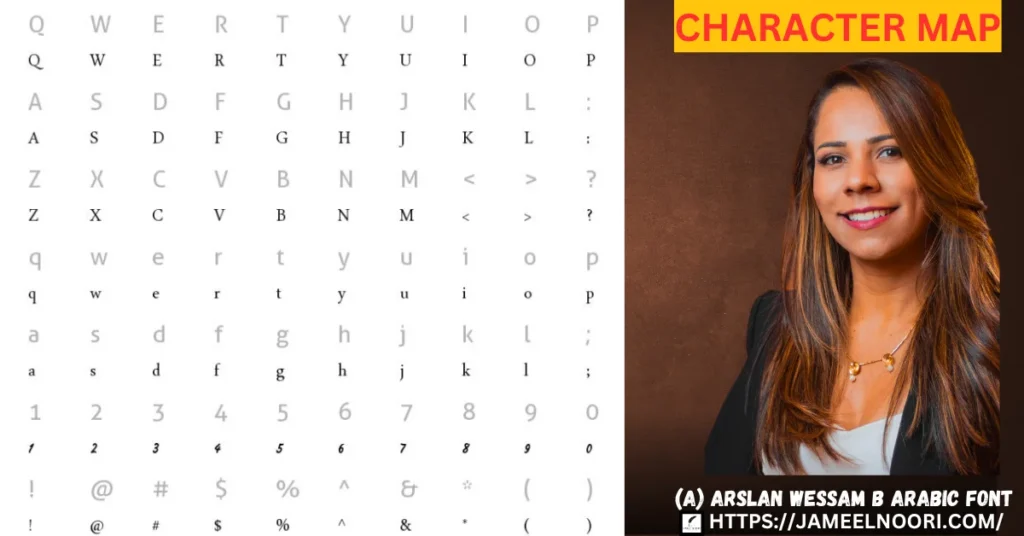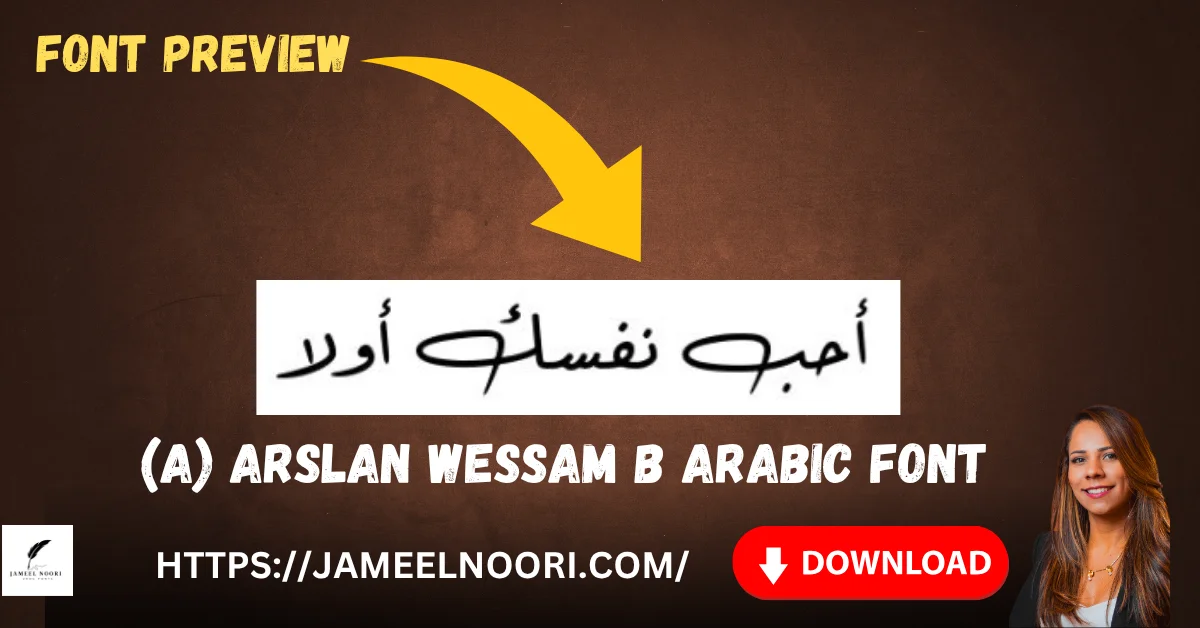
What is (A) Arslan Wessam B Arabic Font?
(A) Arslan Wessam B Arabic Font ek versatile Arabic font hai jo Arabic script se inspire hai. Ye font Urdu script ke similar characters adopt karta hai aur har type ke Arabic writing style ke liye compatible hai.
- Elegant and professional Arabic calligraphy
- Ideal for posters, messages, presentations
(A) Arslan Wessam B Arabic Font ka use karke aap apne designs aur presentations ko professional aur eye-catching bana sakte hain. Ye font designers aur content creators ke liye best option hai.
- High readability for Urdu and Arabic text
- Multiple writing styles supported
- Perfect for social media posts and graphics
Character Map section me aap font ke har character aur calligraphy style ko detail me dekh sakte hain. Ye feature designers ke liye bohot helpful hai.
Why A Arslan Wessam B Arabic Font is Best Choice in Pakistan
Pakistan me Urdu fonts aur Arabic fonts ka use educational aur design purposes me ziada hota hai. (A) Arslan Wessam B Arabic Font ko select karne ki wajah ye hai:
- Best Arabic font for presentations and posters
- Compatible with Urdu fonts for easy writing
- Widely used in Lahore, Karachi, and Islamabad
- Perfect for Islamic calligraphy projects
(A) Arslan Wessam B Arabic Font ek ultimate choice hai un logo ke liye jo Urdu aur Arabic fonts me professional aur stylish designs create karna chahte hain. Ye font highly readable, versatile, aur easy to install hai. Aap chahe social media post banayein ya PowerPoint presentation design karein, ye font aap ki har requirement ko perfectly meet karta hai. Is font ko download karke aap apne designs ko next level pe le ja sakte hain.
Is this font suitable for Urdu writing?
Yes, it resembles Urdu script and works perfectly for bilingual text.
Is this font good for social media posts?
Yes, it creates professional and eye-catching posts.
Does it support multiple writing styles?
Yes, it supports all five Arabic script writing styles.